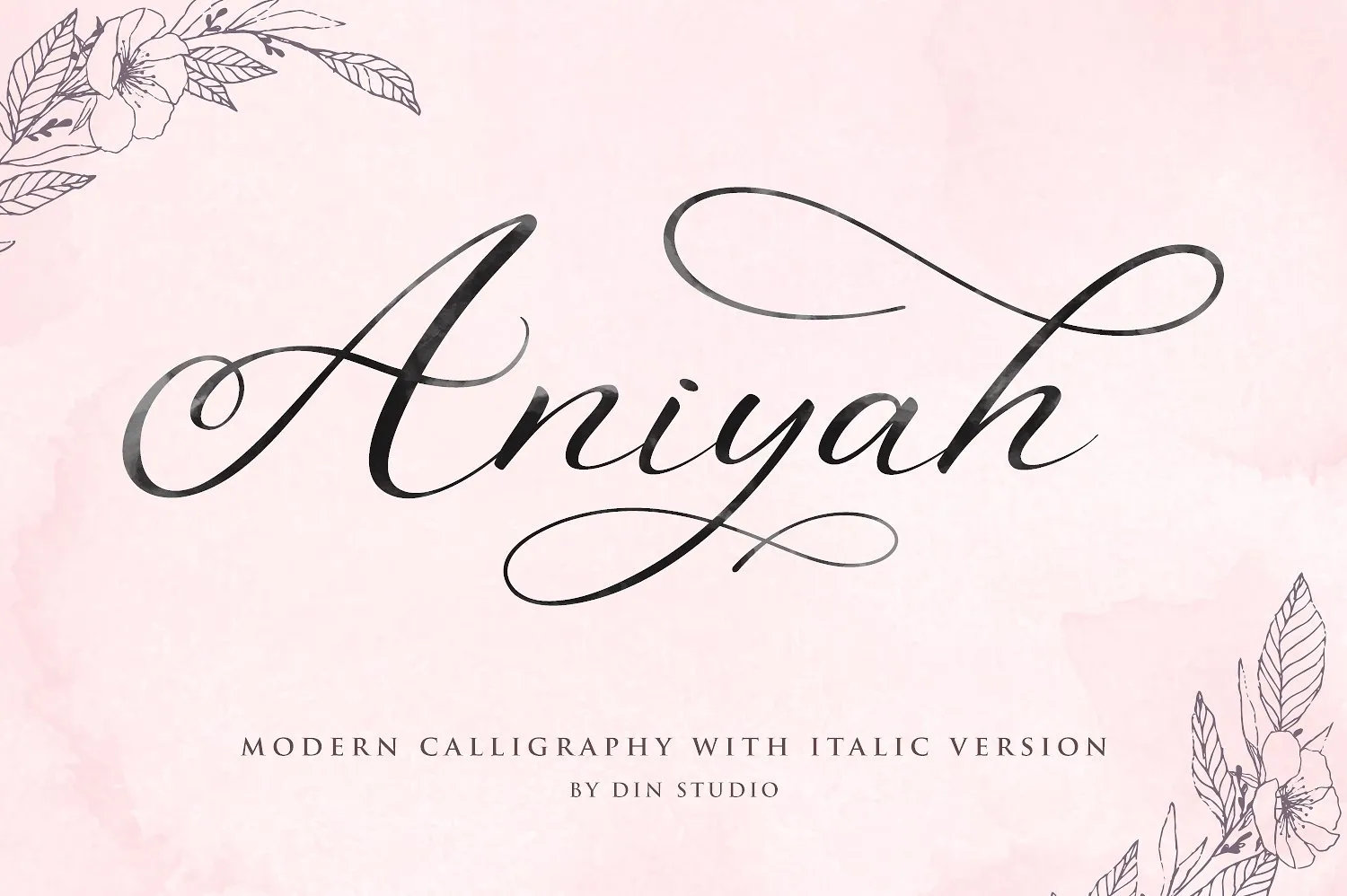
Aniyah Calligraphy Font
A Aniyah Font é uma escolha excepcional para quem busca estilos modernos na tipografia. Com a versão itálica, ela traz uma experiência única que vai além das fontes convencionais. Esta é a fonte perfeita para aqueles buscando um equilíbrio entre o autêntico e o contemporâneo no design de materiais como cartões de aniversário, embalagens de marca, cartões de visita, citações, panfletos e muito mais. Desenvolvida pelo Din Studio, Aniyah é uma fonte de estilo script que incorpora a essência da escrita manuscrita natural e adota um toque moderno. Com sua aparência elegante e contemporânea, ela traz para você um design tipográfico vibrante e sofisticado. Seja em um projeto de cartão de aniversário delicadamente personalizado ou uma campanha de marketing com uma identidade visual inovadora, Aniyah vai transformar seu trabalho. A fonte é ideal tanto para aqueles buscando criar algo tradicional quanto para aquelas pessoas que estão sempre à frente da tendência. Intrinsecamente ligada à arte da escrita manuscrita, a Aniyah traz uma vivacidade e um brilho único para cada projeto em que for usada. Afinal de contas, quem não adoraria receber cartões de aniversário com uma elegância cuidadosamente planejada? Esta fonte é perfeitamente capaz de fazer isso possível, dando ao seu design um toque autêntico e moderno ao mesmo tempo.